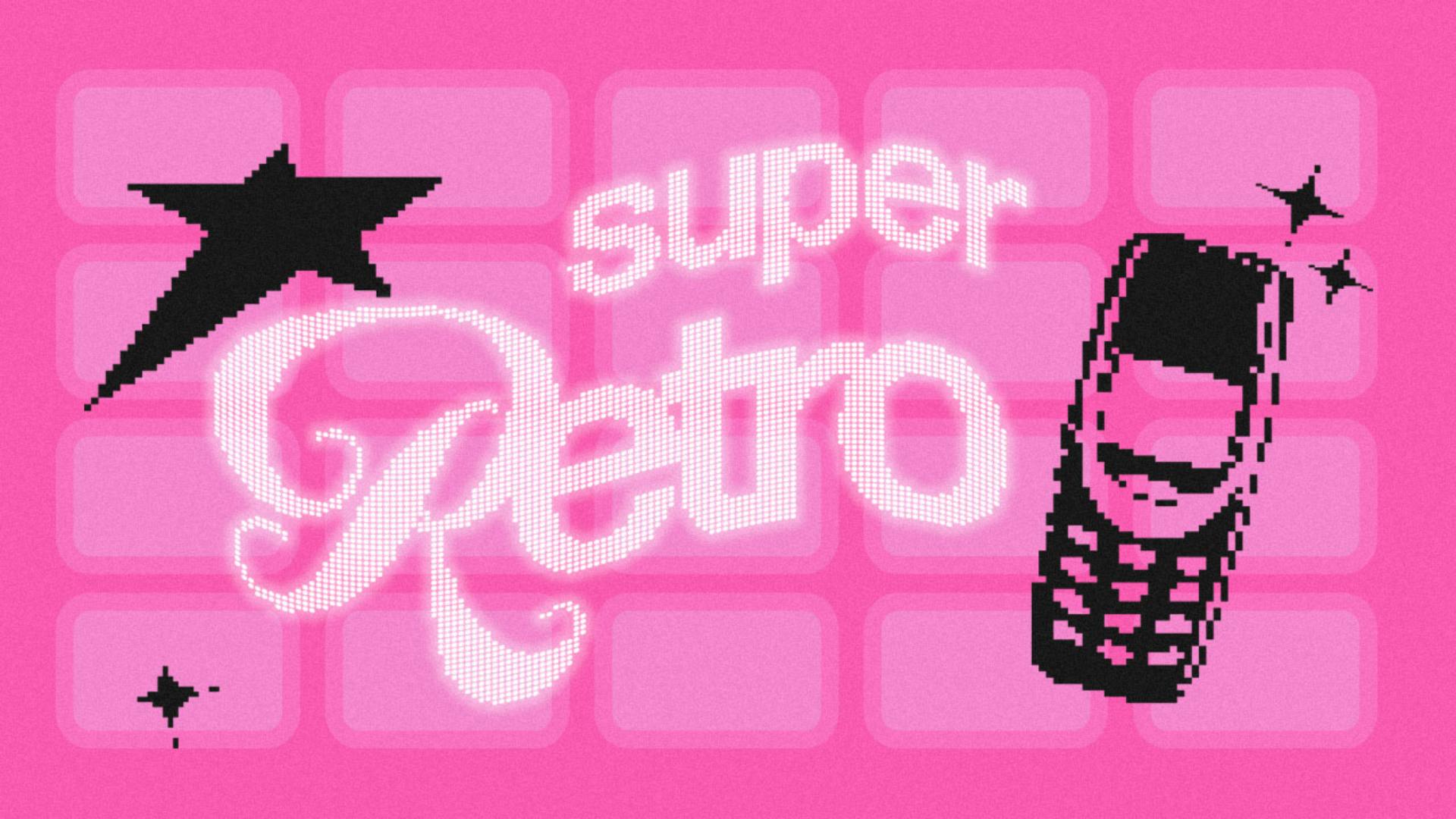
El estilo Y2K ha llegado para revolucionar el diseño gráfico. Colores y texturas vibrantes, efectos metalizados, pop y holográficos se combinan con guiños a los primeros celulares y a las páginas web de comienzos de siglo ¿El resultado? Piezas futuristas-pop, píxeles por todos lados y una fusión retro-tecno divertida e impactante. En este tutorial aprenderás a crear arte pixelado de forma ágil y eficaz, como si estuvieras tipeando un SMS a principios del 2000.
Super retro: arte pixelado y con mucho carácter
Las tipografías son un elemento clave en esta nueva ola de diseño retro-futurista y nostálgico. Durante los años 90 y principios de los 2000, las fuentes se destacaban por sus ángulos marcados, formas geométricas y diseños audaces.
En este tutorial, Ari Marasco propone un ejercicio de síntesis visual en donde además de aprender a darle a las tipografias el estilo Y2K, aprenderás, paso a paso, a simplificar elementos, tomar decisiones de color y transformar formas complejas en composiciones de estilo pixelado.
A partir de un póster diseñado especialmente por ella para este tutorial, comenzarás convirtiendo un archivo PNG (la foto de un celular) en un gráfico vectorial monocromático con estética pixel-art. La siguiente etapa, consta en editar las tipografías para llevarlas de lleno a los 2000: pixelizarlas y aplicarles efectos de movimiento y brillo, cargados de la nostalgia de la época. Las herramientas clave del proceso son “Edición global” y “Crear mosaico de objetos”, dos recursos que, si aún no usabas, después de este tutorial vas a querer aplicar siempre.